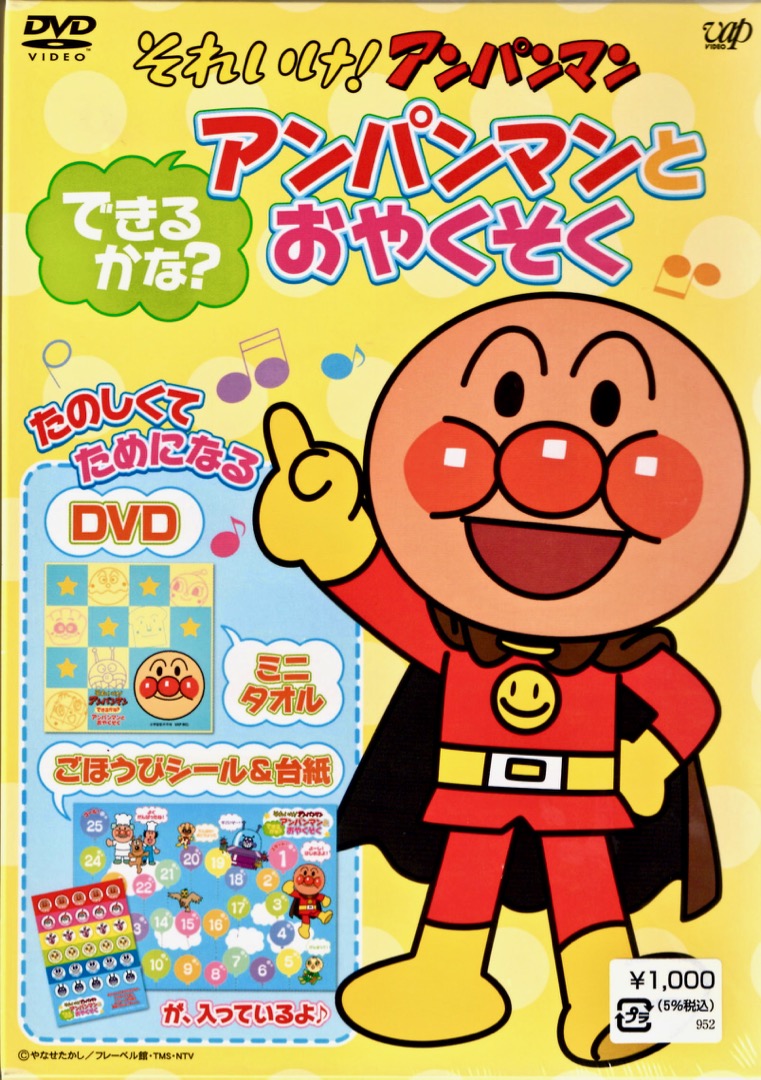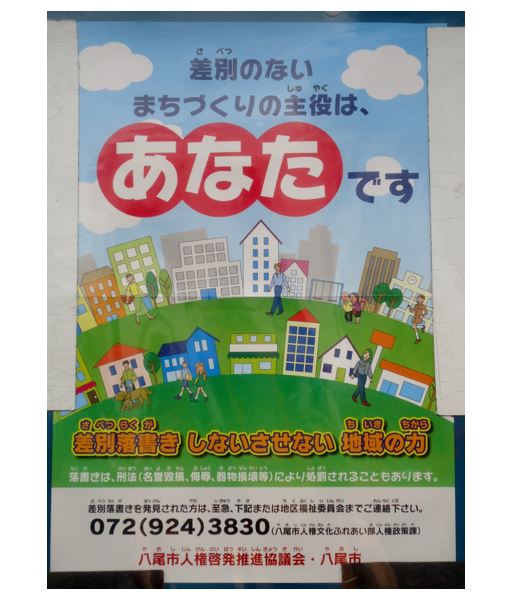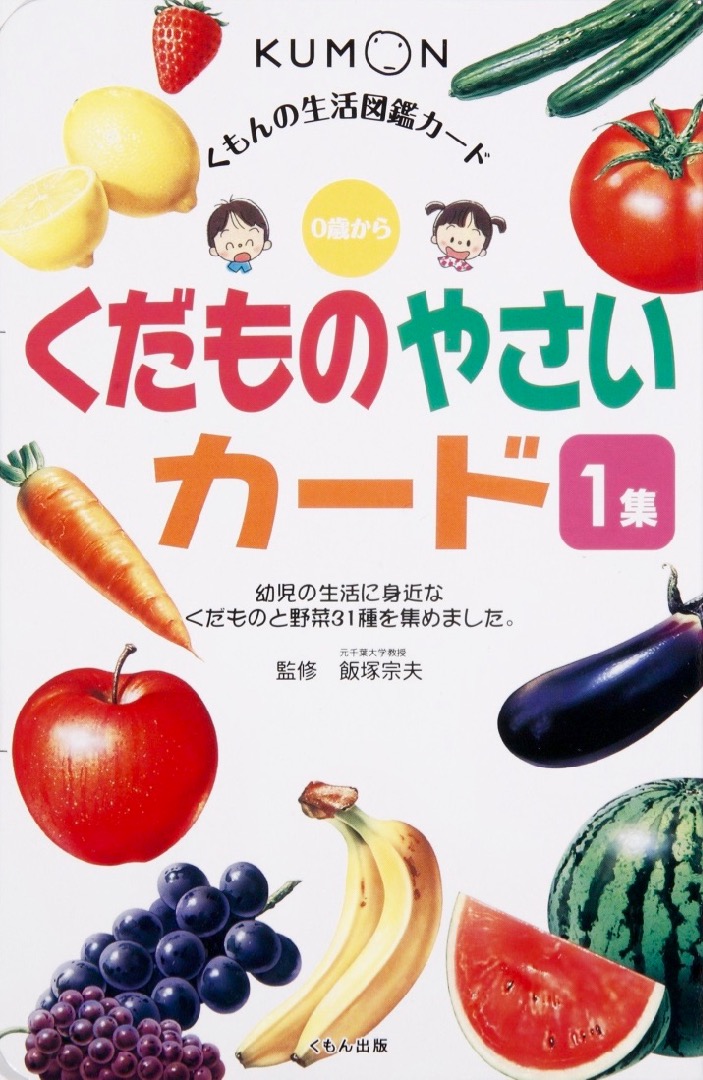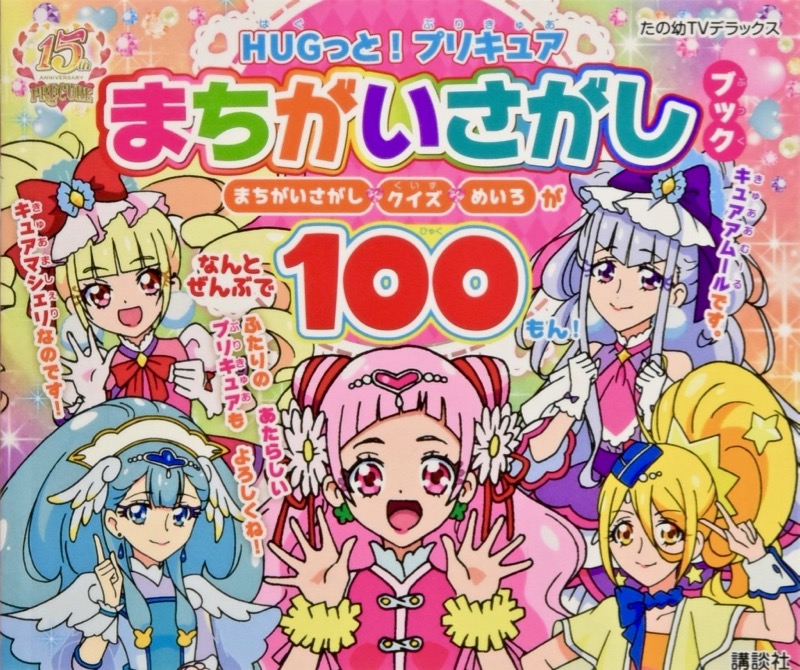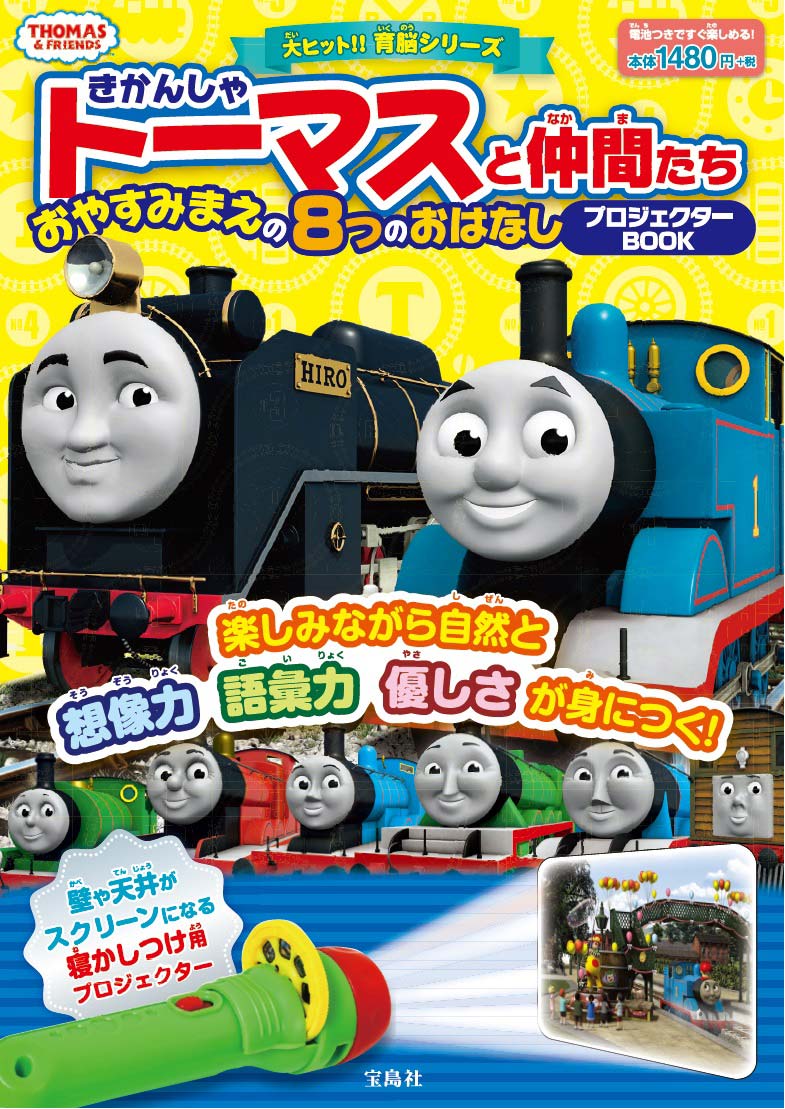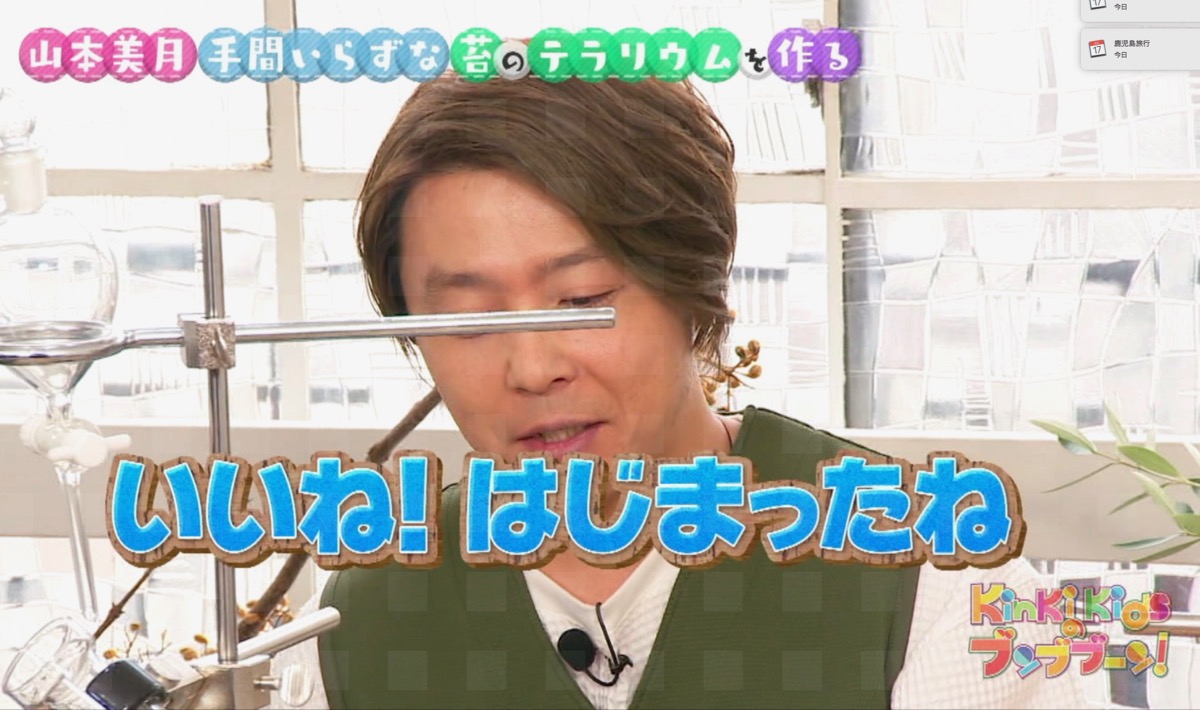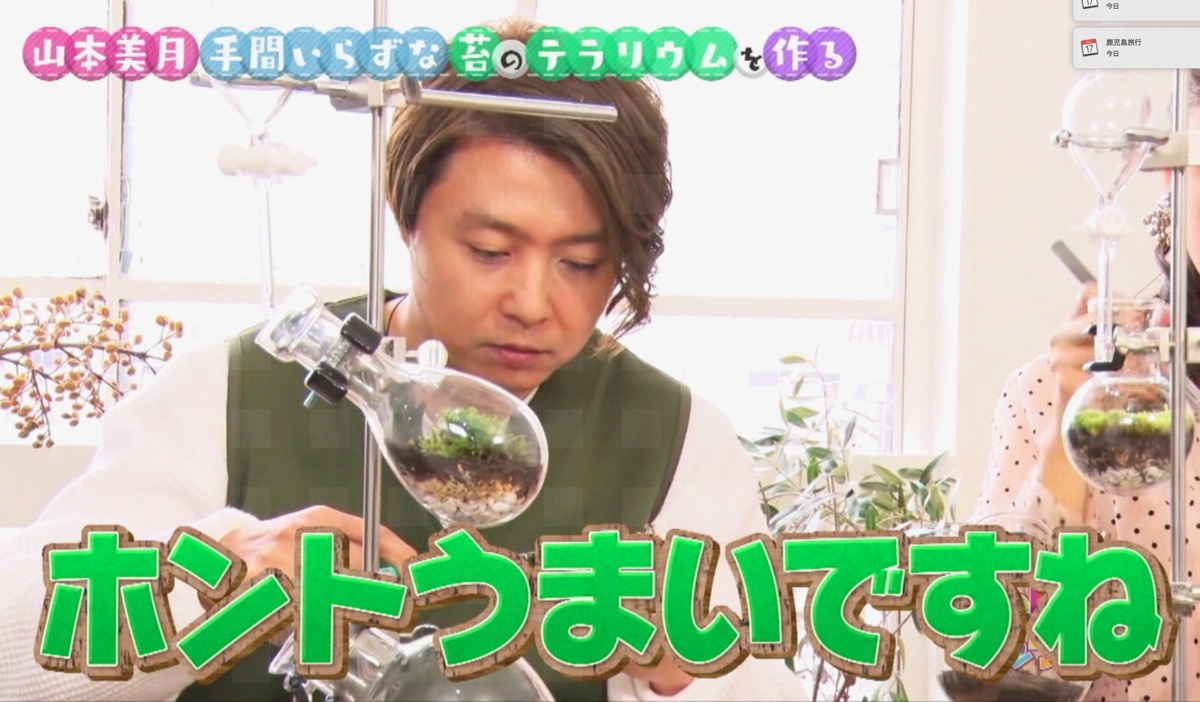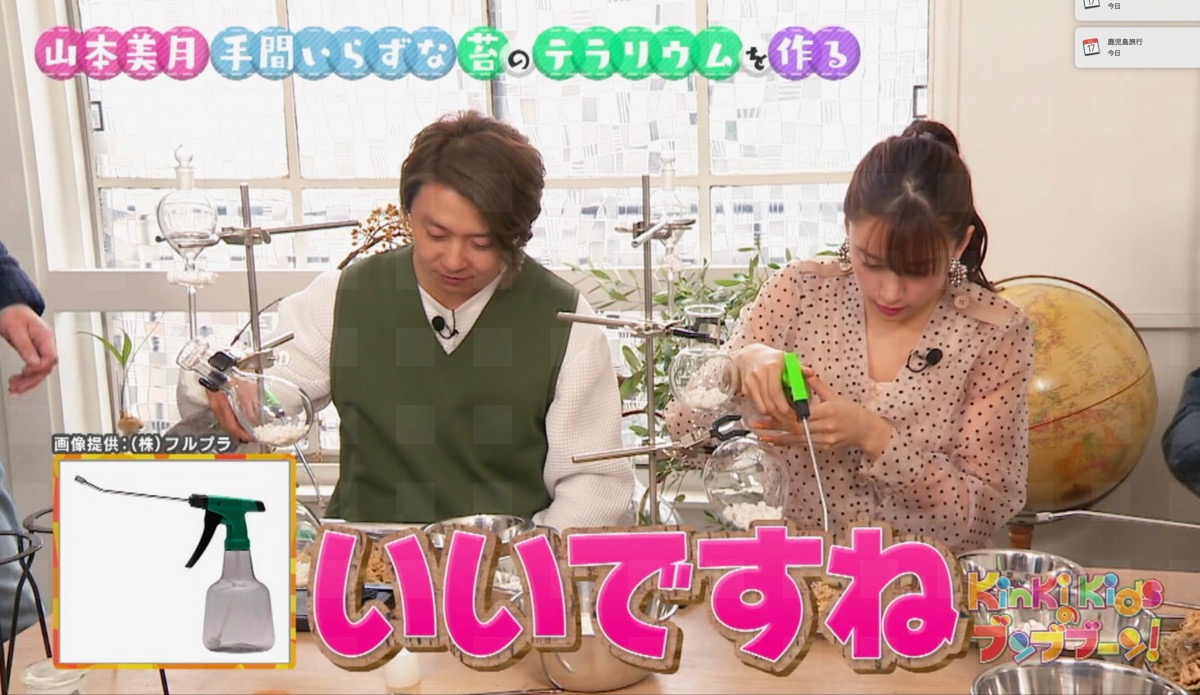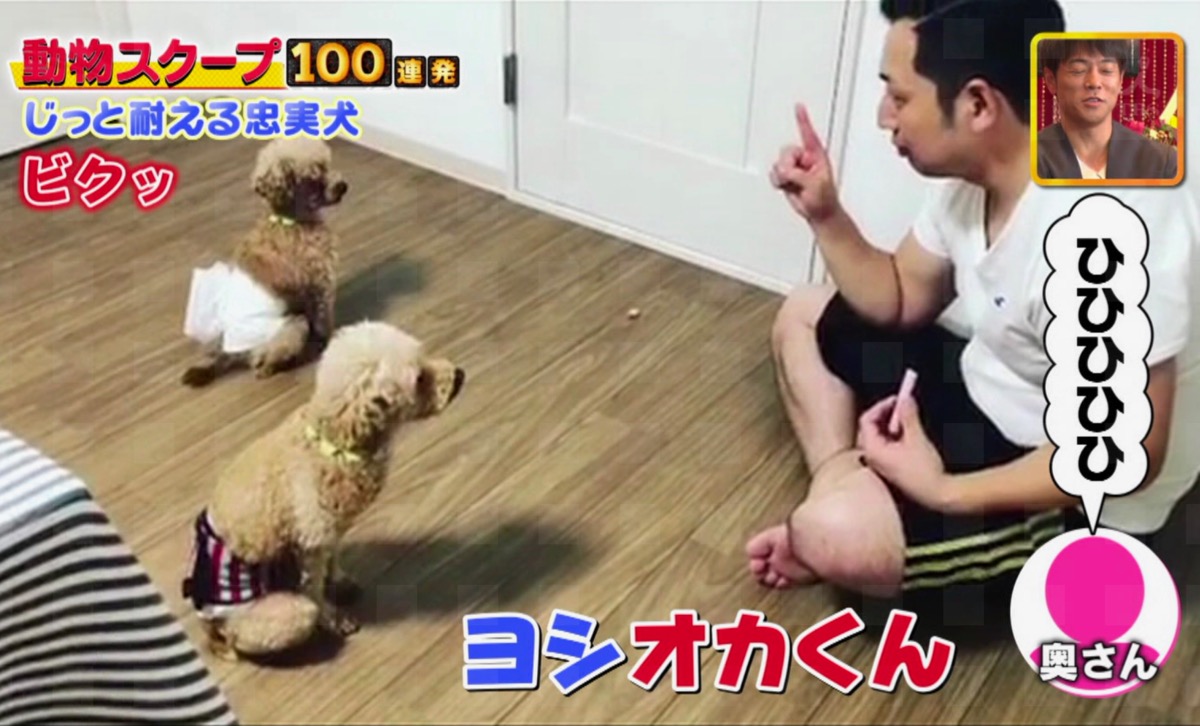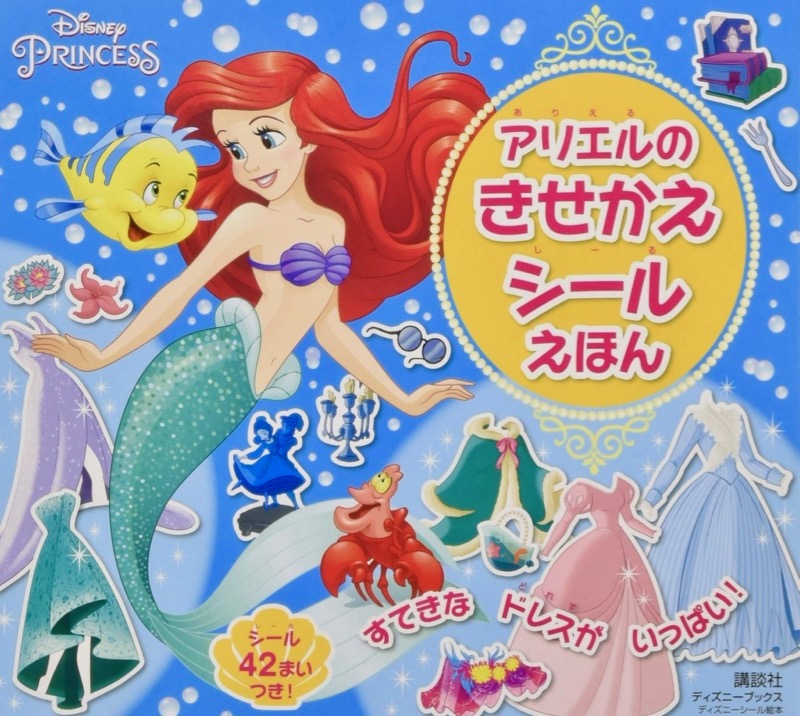
佐藤さん、こんばんは。
小島よしおによるYouTubeチャンネル「ピーヤの休日」の動画で「ハッピールイカ」書体がたくさん使われています。
ウェイトは一番太い09でしょうか。
◎画像はこの動画より↓
参考にもう1枚。
特徴的な「1」もそうですが、「」や『』のデザインとか、半濁点「゜」の大きさや付け方からも他社にライセンスされているハッピー書体と違う「ハッピールイカ」だと判別できますね。
ハッピールイカの雰囲気は、小島よしおの芸にピッタリな感じです。
タイプラボのフォントは、youtuberたちに好まれていますね。
書名:シャチのラビーママになる
著者:井上こみち
発行:国土社
日本テレビ「有吉の壁」だったかな。
書名:たたかうざーやくマン
著者:なかきたひでき、磯山恵一
発行:銀の鈴社
NHKの「鑑定!どうぶつ不動産」。
書名:「ずぼら」ママでも、結局すべてうまくいく!
著者:三浦直子
発行:Clover出版
KFCのプリペイドカード。
「言」の文字でハッピールイカと判る。
英字も含めすべてハッピールイカ。
春日市ふれあい文化センターが発行の情報誌。
書名:ごみとわたしたち
発行:福岡市こども環境局
書名:ぼくたちのおばけえんとつ
著者:文・櫟原文夫 絵・中尾里穂
発行:NPO法人千住文化普及会